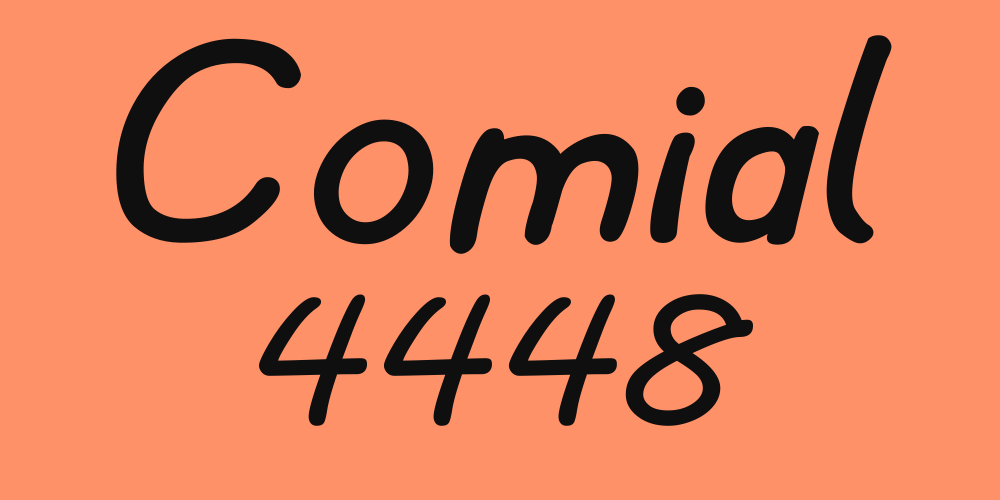
Comial 4448 font
A ‘Comial 4448’ é uma fonte sans-serif que combina a essência do clássico com a modernidade, embora possa parecer algo diferente ou até estranho devido à sua grande escala, com aproximadamente 4400+ caracteres. Embora seja designada como uma fonte sans-serif, ela se assemelha mais a uma fonte Unicode, o que torna cada letra e caractere singularmente único, dando ao texto um ar inusitado e vibrante. Hamilton é o designer desta fonte, oferecendo um resultado que não apenas abrange uma ampla gama de caracteres, mas também reflete as possibilidades criativas do Unicode. Este design pode ser particularmente útil para projetos exigentes que precisam de uma grande variedade de símbolos e letras em um único arquivo. Com a ‘Comial 4448’, designers e profissionais da área podem explorar a essência única desta fonte, que se destaca tanto por sua abrangente capacidade quanto pela personalização inovadora proposta pelo designer Hamilton.